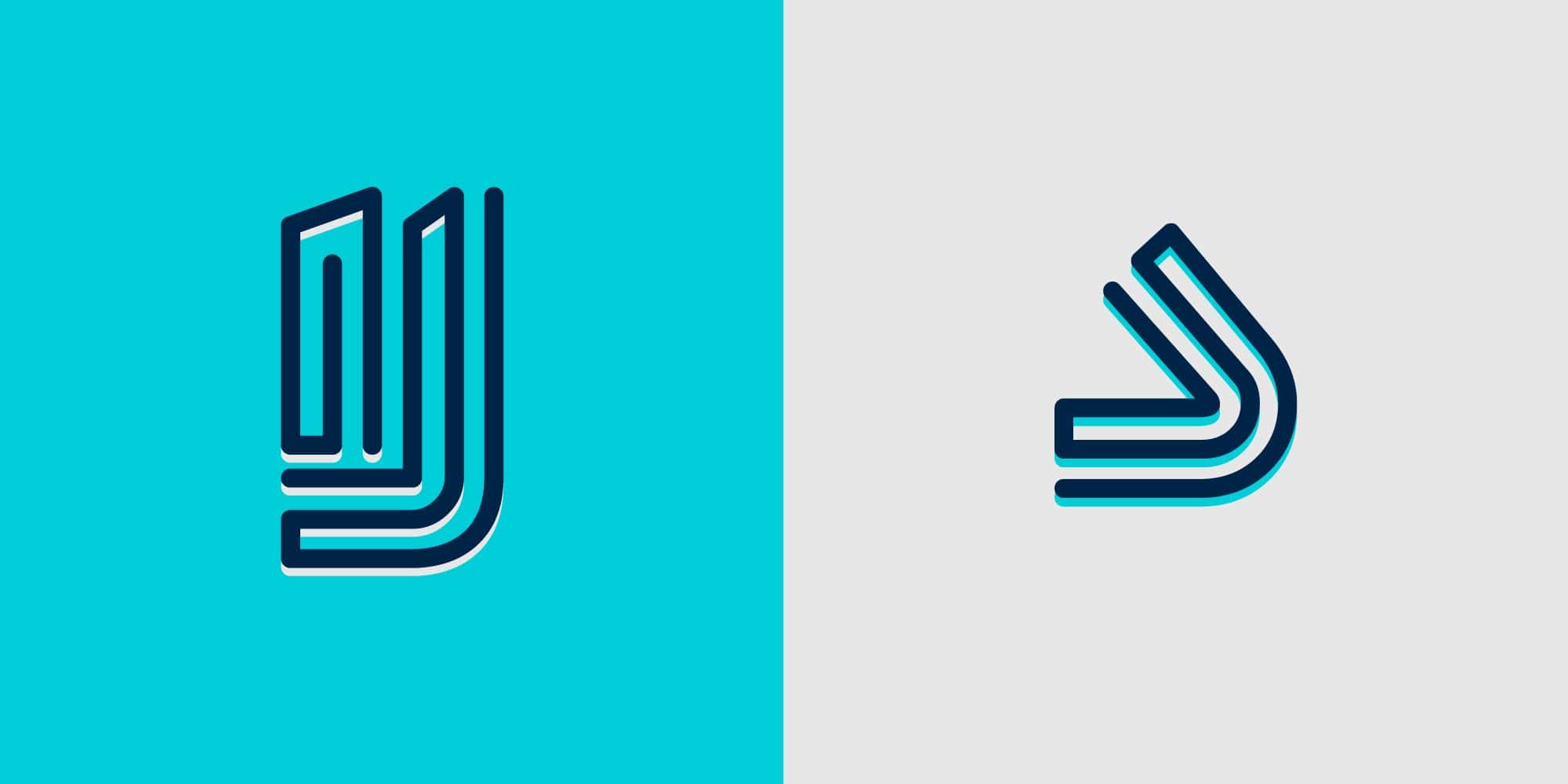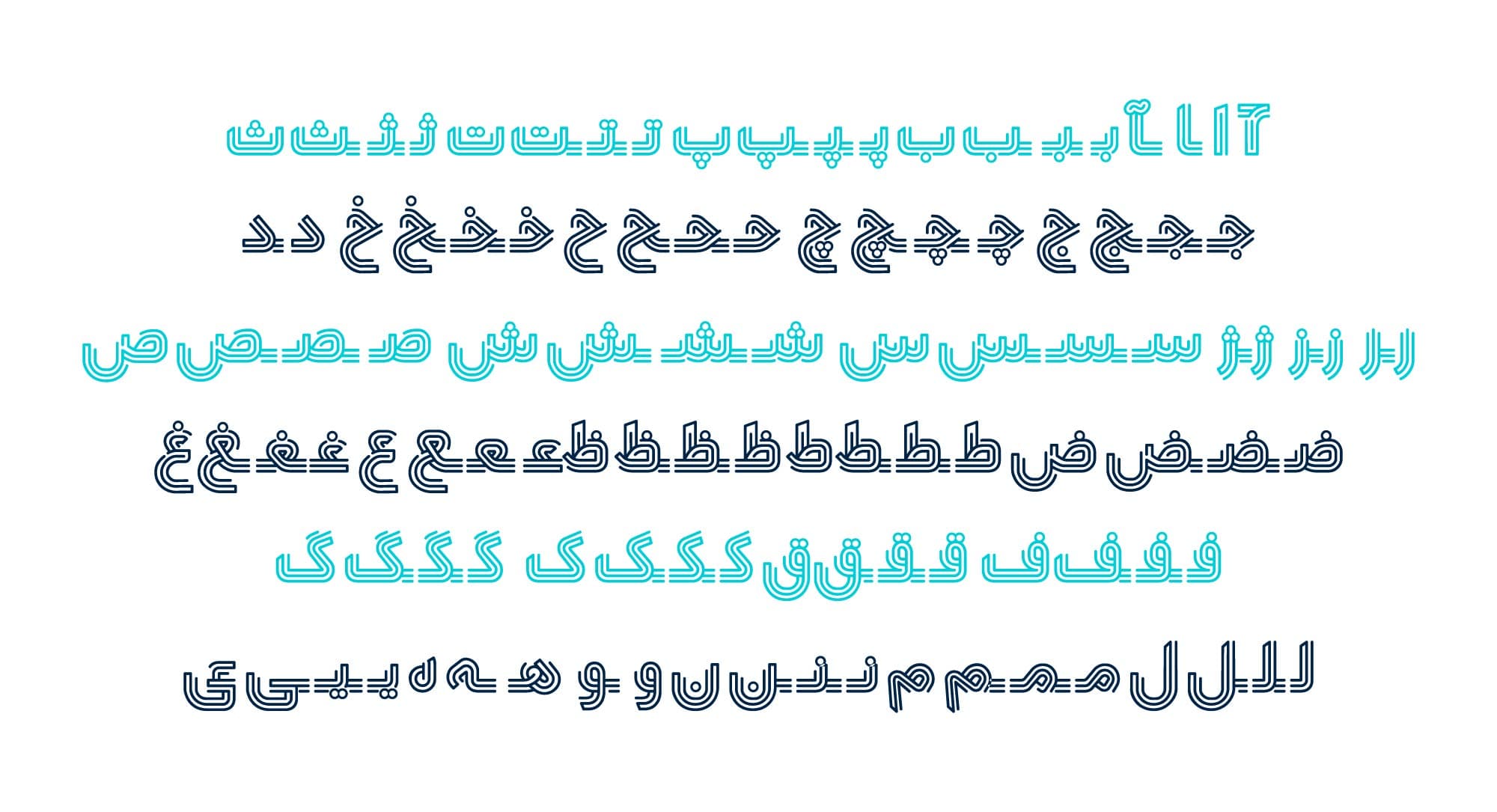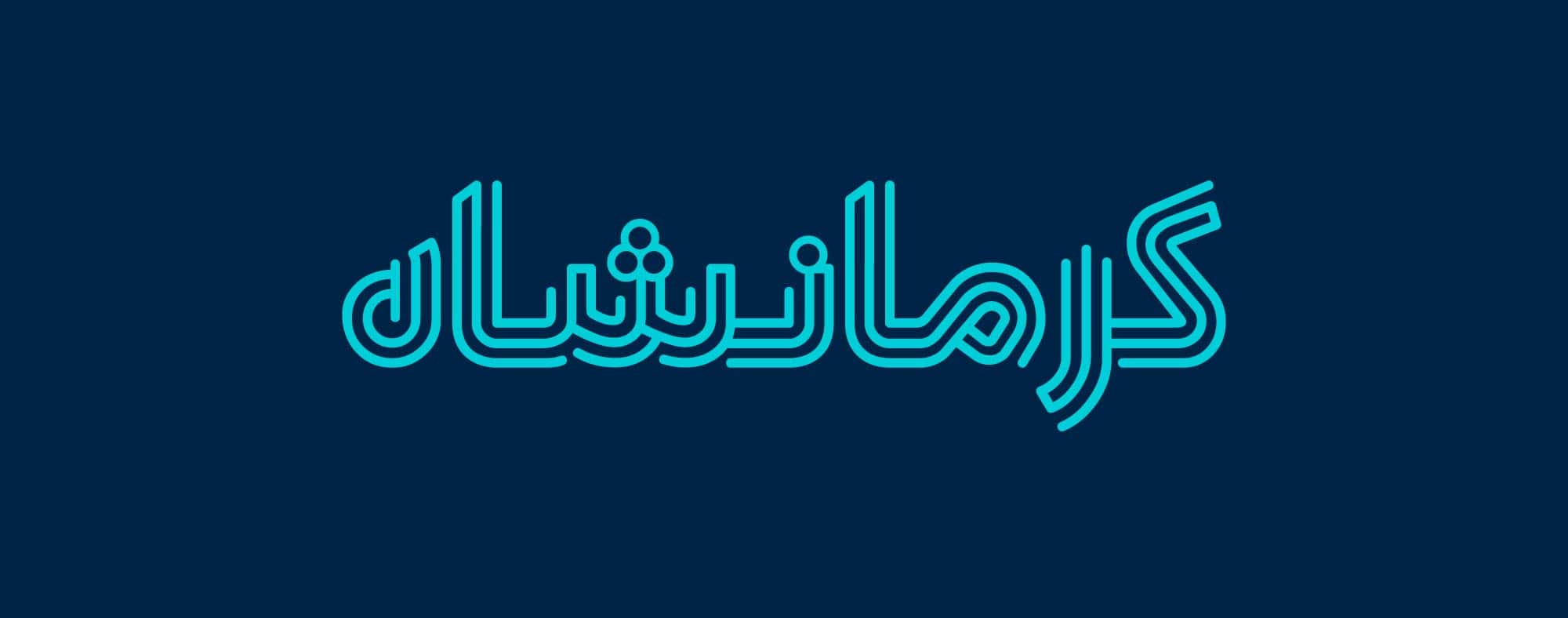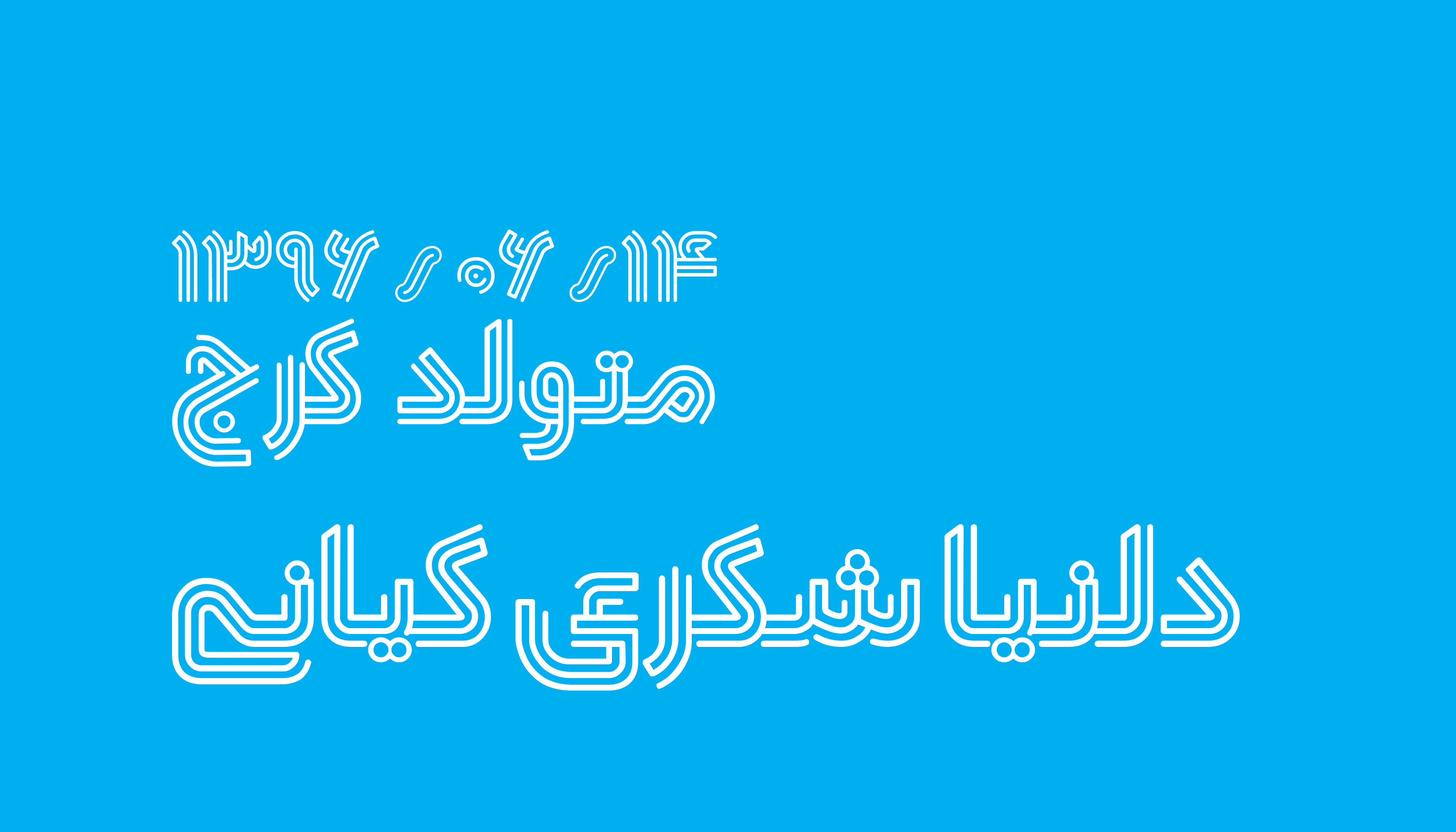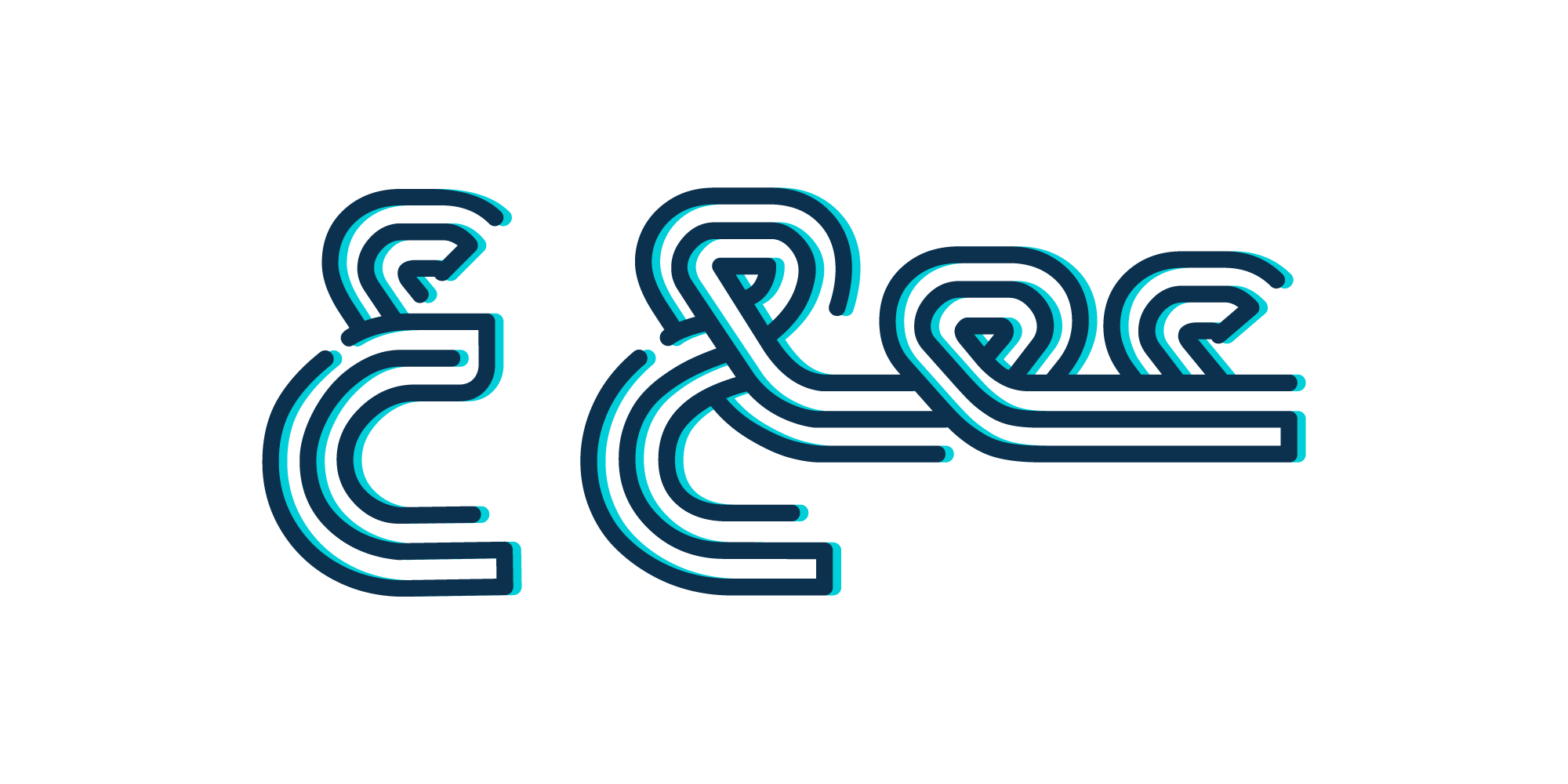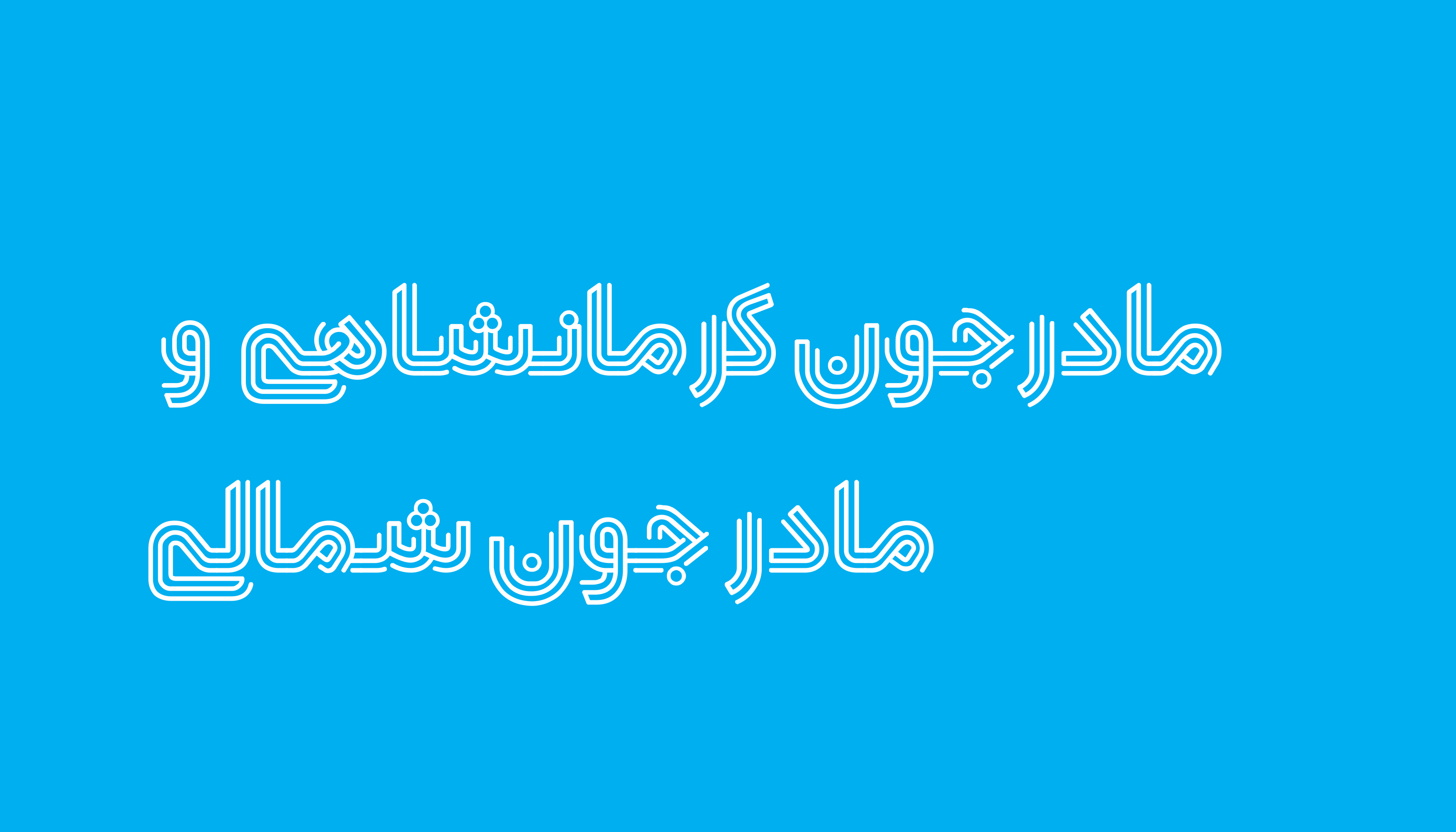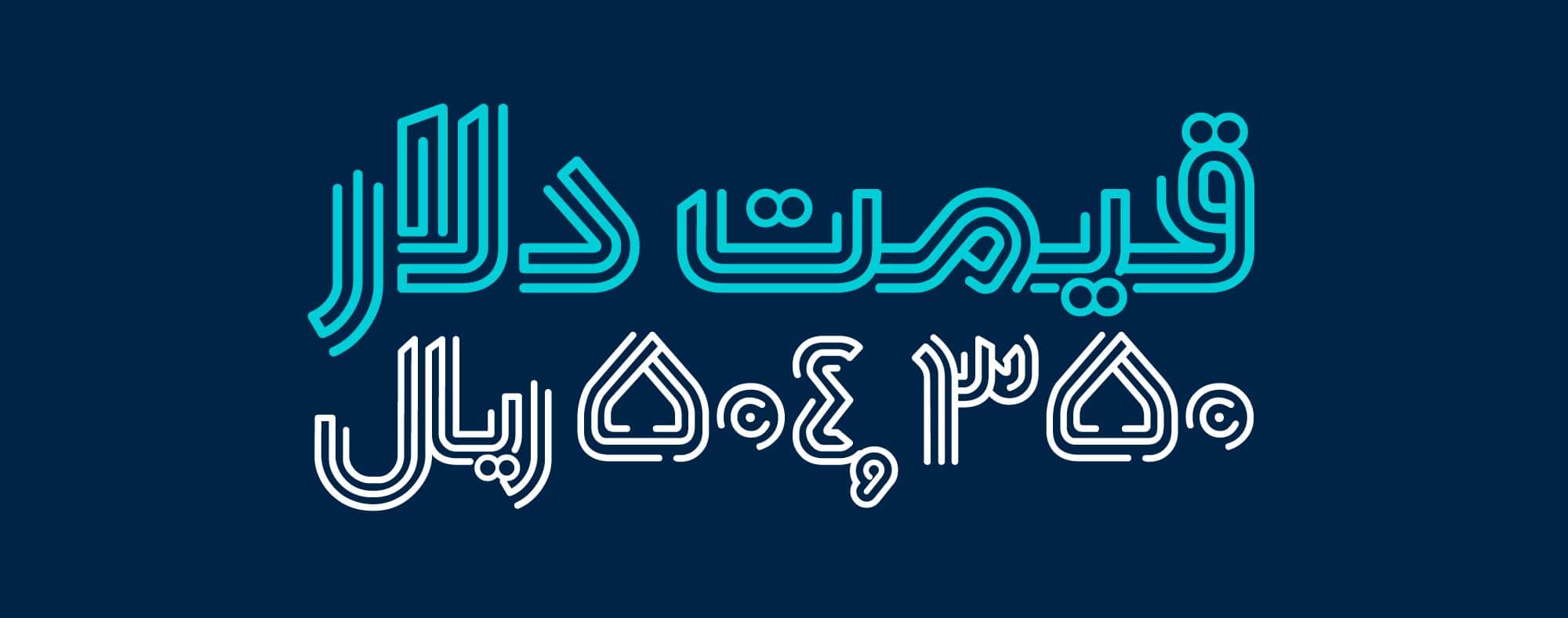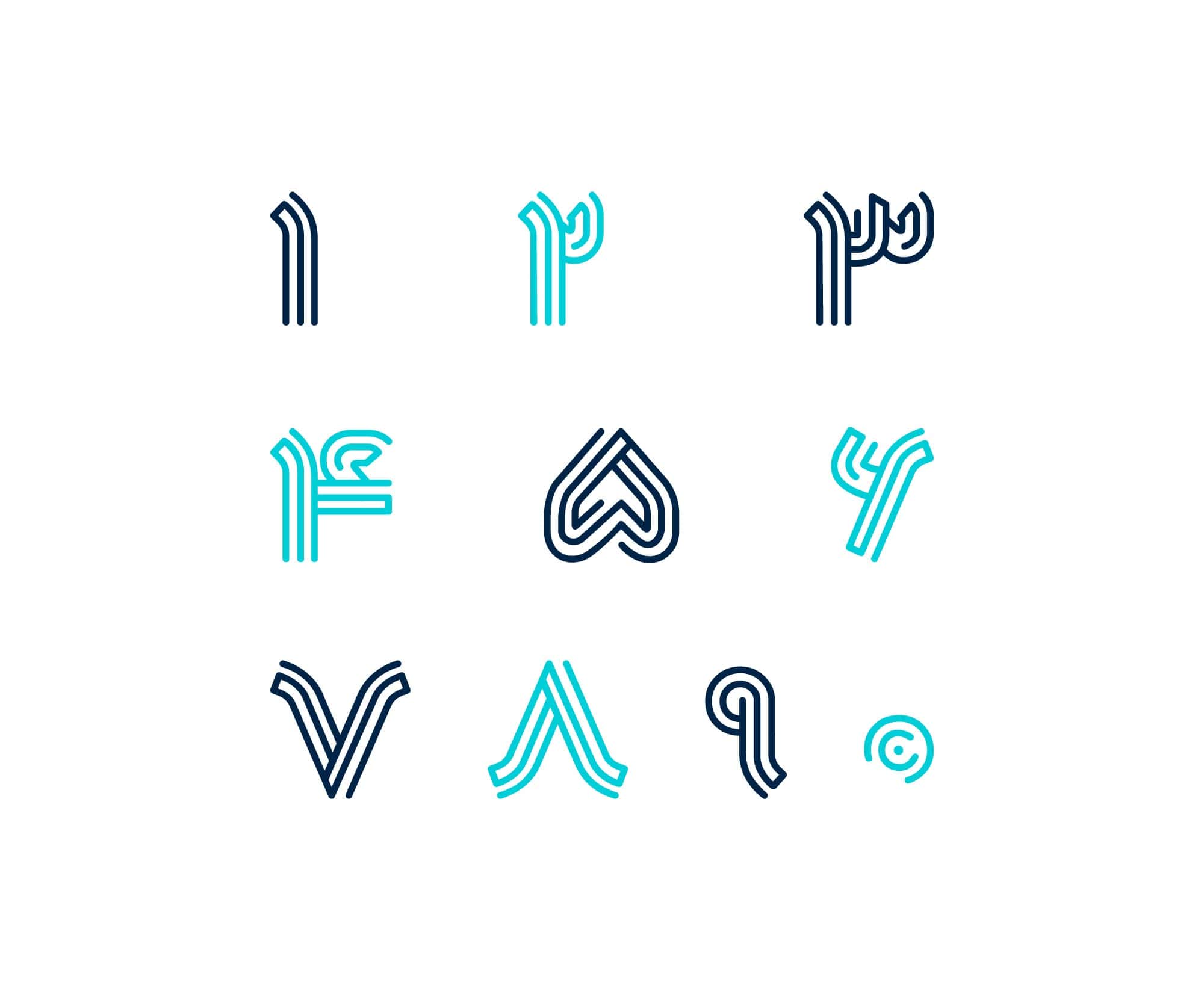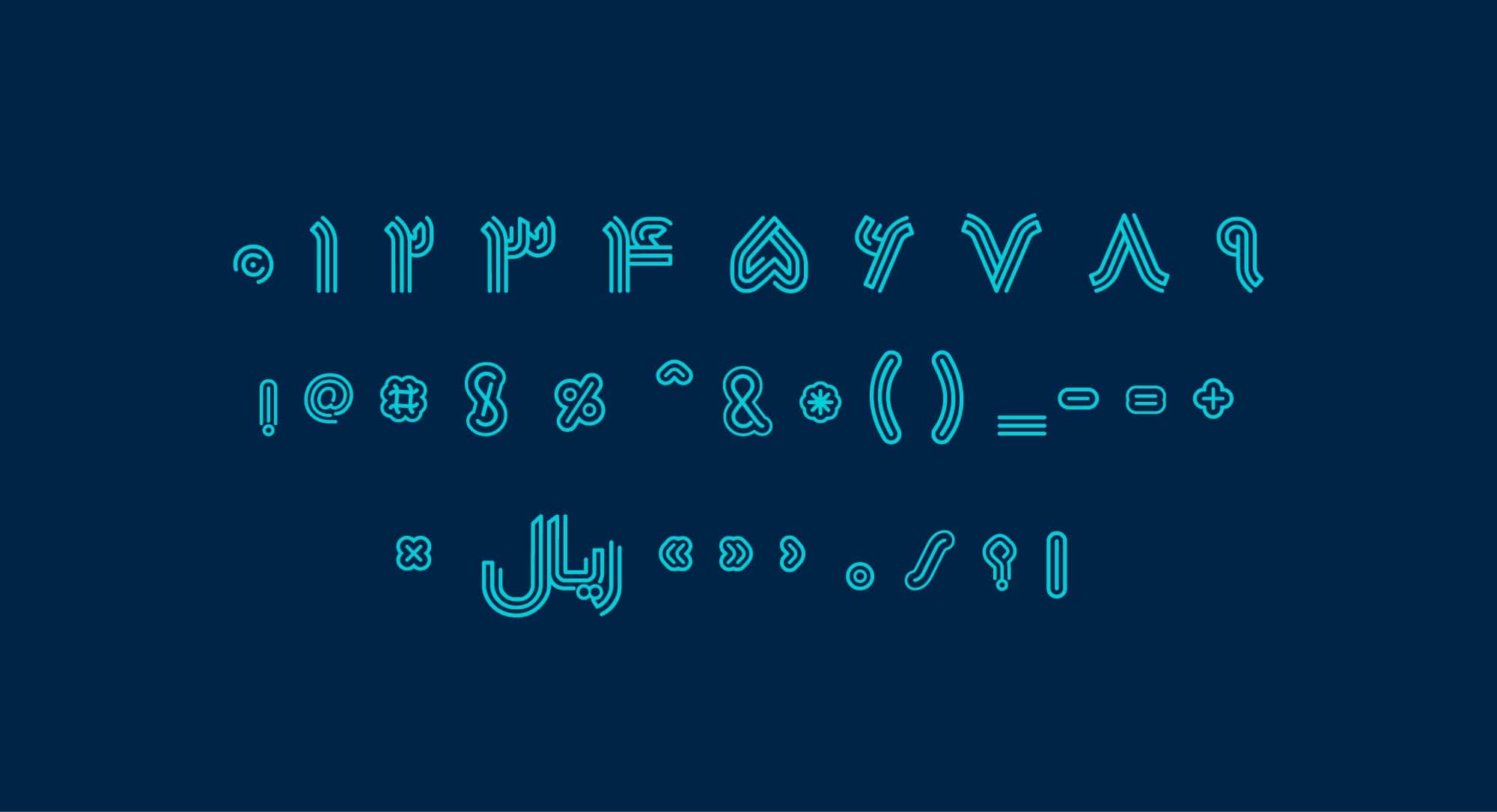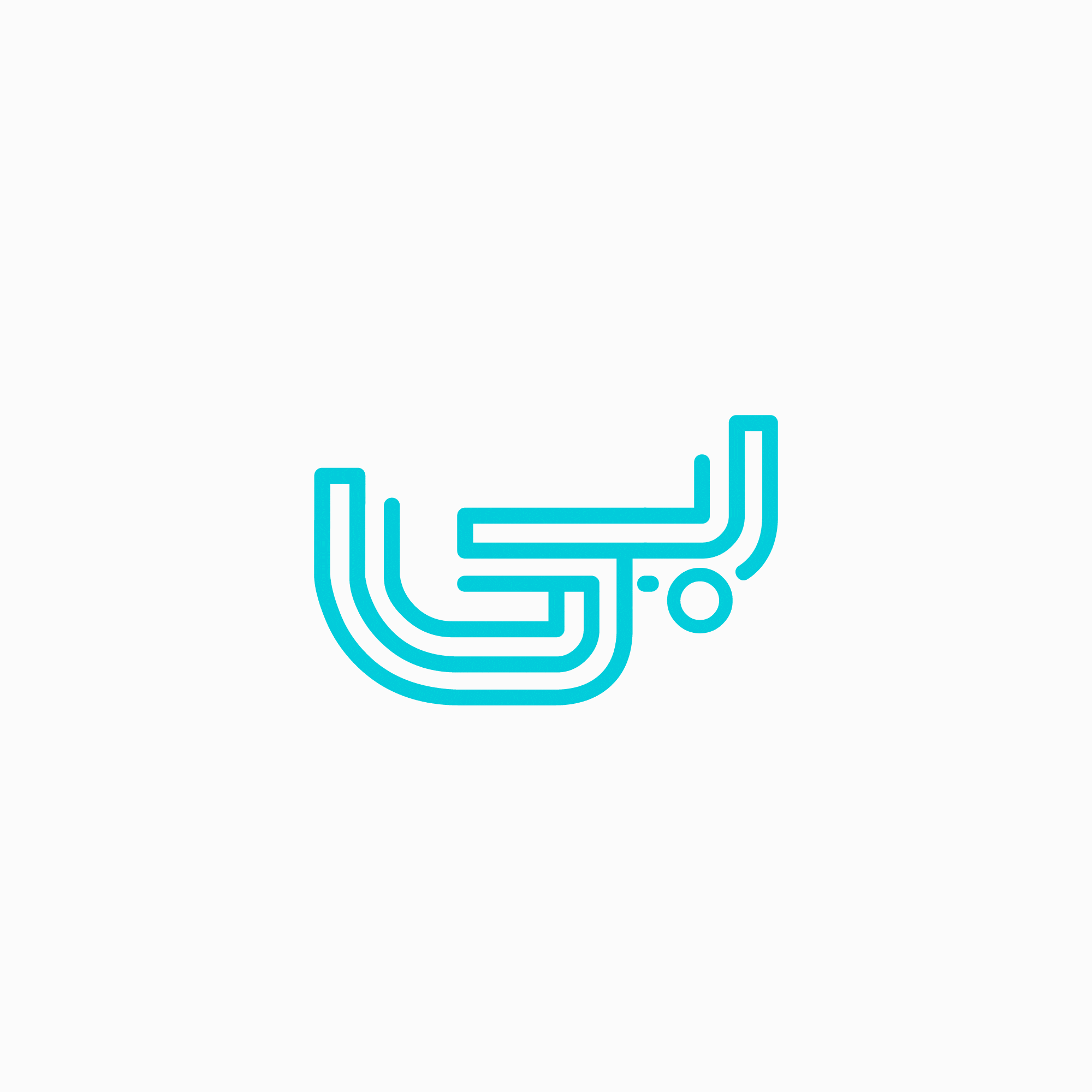
فونت در دنیای امروز هم چون دیگر ابزارهای نوشتار صورت دیداری گفتار است که یکی از مهمترین نقشهای آن به عنوان ابزاری کمک حافظه، جهت به خاطرسپاری اطلاعات دانست. بر این اساس میتوان این گونه بیان نمود که شکل دیداری فونت علاوه بر تسهیل در امر خوانش میبایست در پردازش و ماندگاری آن نیز نقش داشته باشد.
با توجه به صورت دیداری فونتها آنها را میتوان به گروه سخت خوان و راحت خوان تقسیم بندی نمود. در طراحی فونت دلنیا هدف اصلی ایجاد مکس و تمرکز خواننده بر محتوای ارائه شده است تا با صرف زمان بیشتر اطلاعات در ذهن مخاطبان ماندگار شود. از این روی با توجه به فضاهای مثبت و منفی و گردش حروف فارسی تصمیم بر آن شد که خطوط بر محیط فرم و گاهاً در داخل فرم هر نویسه گردش کرده و با ایجاد برشهایی منطقی در فرم نویسه ها، این فرصت در اختیار مخاطب قرار داده شود که ذهن او فرم حروف را تکمیل نماید. که این امر مُنجر به افزایش زمان، جهت مطالعهی محتوای مورد نظر را در پی دارد و در نتیجه محتوا نیز در ذهن او ماندگارتر میشود.
فونت دلینا براساس آزمون لغات در گروههای سنی مختلف مورد آزمایش قرار گرفت و نتیجه آزمایش فوق مطالب پیشین را تأیید نمود.
به لحاظ کاربرد، فونت دلنیا جهت استفاده در تیترهای بلند و کوتاه طراحی شده است. در طراحی فونت به حرکت خطوط و چگونگی اتصال هر نویسه دقت شده است که شکل متصل و منفصل حروف یکسان بوده و خطوط کرسی در کلمات به حداقل برسد که این امر مُنجر به نظم بصری بیشتری در جملات می شود.
لازم به ذکر است که فونت دلنیا علاوه بر زبان فارسی از زبان کُردی و عربی نیز پشتیبانی می کند.